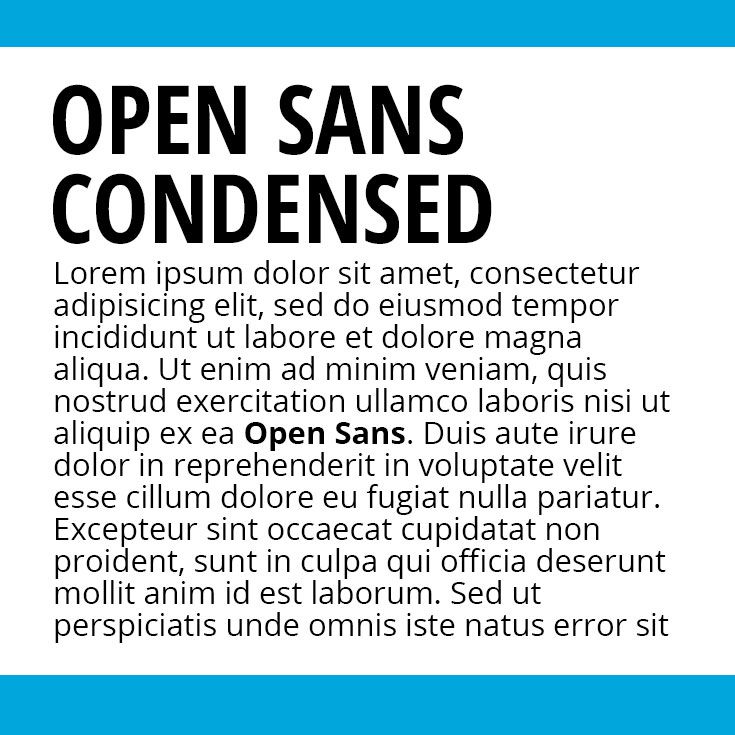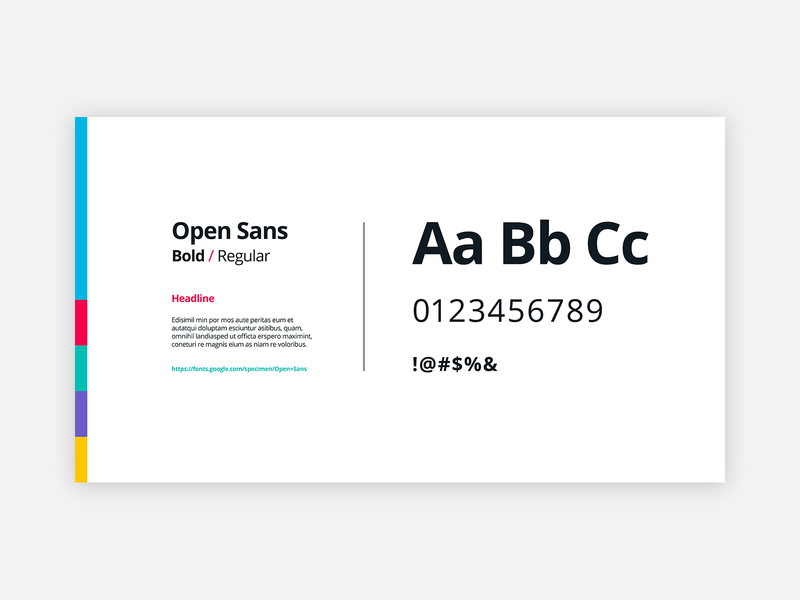
Open Sans, единственный шрифт, который вам когда-либо понадобится
Open Sans — это чистый и современный шрифт без засечек, разработанный Стивом Маттесоном по заказу Google. Он специально разработан для удобочитаемости в печатных, веб- и мобильных интерфейсах.
Open Sans отлично подходит для любого типа использования. Он невероятно удобочитаем в небольших размерах, а также отлично работает при печати большими буквами. Лучше всего то, что это бесплатный шрифт! Вы можете бесплатно использовать и загружать его для своего следующего дизайнерского проекта.
Это хорошо известный и современный шрифт, который все чаще используется на новых веб-сайтах. Из-за своей простоты он действительно делает ваш контент легко читаемым. То же самое касается офлайн-контента. При печати это сделает ваши документы потрясающими.
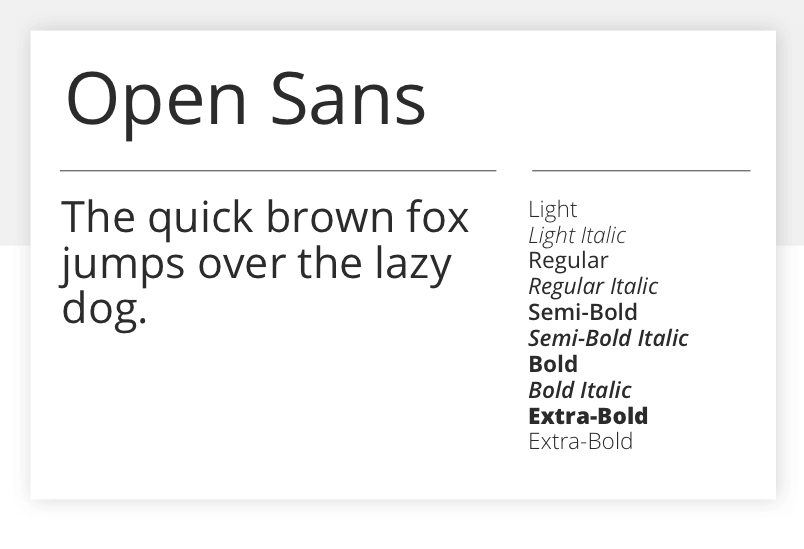
Font Park
Если вы когда-нибудь мечтали о поисковой системе только для шрифтов, вы будете рады открыть для себя Font Park. Ищите шрифты для каллиграфии, надписи в греческом стиле или даже шрифты из научной фантастики. От штрих-кода и шрифта Брайля до еды и огня — вы найдете всевозможные невероятные шрифты, когда начнете копаться в Font Park.
Великолепные изображения, интуитивно понятный дизайн и привлекательные цвета — все это аспекты, которые в совокупности создают привлекательный и функциональный веб-сайт. Но есть еще один не менее важный компонент — ваш выбор шрифта.
Знание того, какой шрифт использовать, может иметь значение для вовлеченных клиентов или разовых посещений. Из множества доступных шрифтов, какие из них окажут оптимальное воздействие?
Обратите внимание, что использование стека системных шрифтов будет означать, что текст будет отображаться с разными шрифтами на разных устройствах. Это может создать проблемы, если пользовательский интерфейс зависит от точного размера текста. Стек системных шрифтов также не рекомендуется, если вам нужен единый шрифт на вашем веб-сайте на разных устройствах для целей брендинга.